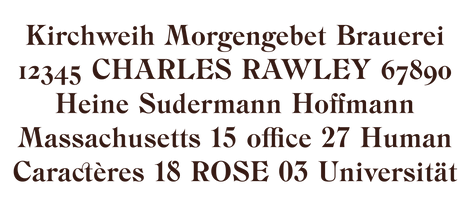
Шрифт Ангелус Медиаваль/DXAngelusMediaval
Гарнитура: DXAngelusMediaval
Тип: Антиква, Акцидентный
Начертание: Regular
Шрифт DXAngelusMediaval разработан на основе рисунка шрифта Ангелус Медиаваль, выпускавшегося русскими словолитнями с начала XX века (возможно Словолитным заведением Г.Бертгольда, С.-Петербург и Москва, ранее 1904 г.). Вероятно, шрифт является переработкой шрифта DeVinne(1892(?), дизайнер Nicholas J. Werner) американской словолитни Central Type Foundry.
В качестве образцов использовались примеры шрифта: кириллица из каталога "Художественные шрифты", 1929 (сканы А.Гофманн из описания к её версии шрифта), латинская часть - шрифт Chicago, из каталога словолитни La Fonderie Typographique Francaise(FTF).
Дополнительно в шрифте спроектированы цифры старого стиля и лигатуры.